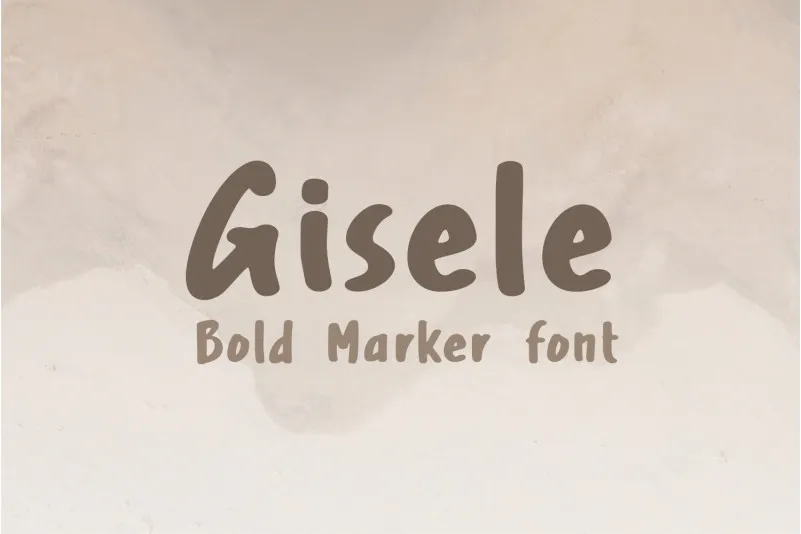
Gisele Script Font – Download Grátis
A Gisele Script Font é uma escrita à mão com traços marcantes que transmitem força e personalidade. Essa fonte foi criada para aqueles buscando uma maneira de adicionar um toque autêntico aos seus projetos digitais. Para quem está procurando por uma opção de letras a mão que não perde o poder de impacto, Gisele Script é uma escolha excelente. A 38.lineart trouxe para nós essa fonte bold e marcante, ideal para criar um visual atraente em elementos como gráficos de mídia social ou design editorial. Para aqueles que apreciam os detalhes do estilo à mão, Gisele Script oferece uma opção única e poderosa no universo das fuentes Handwritten Fonts.